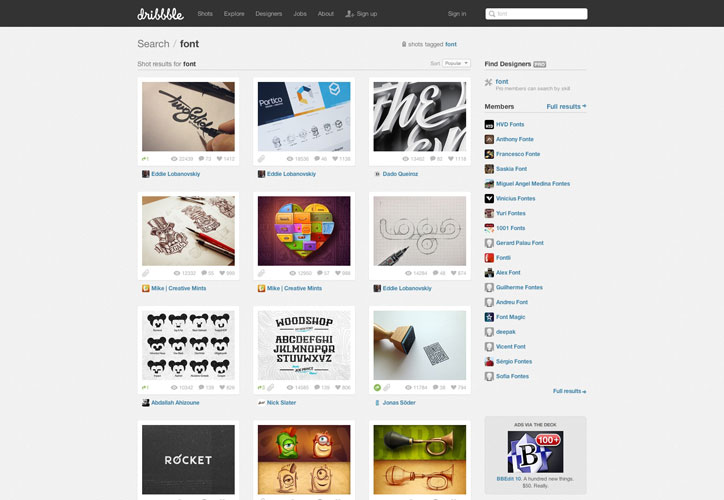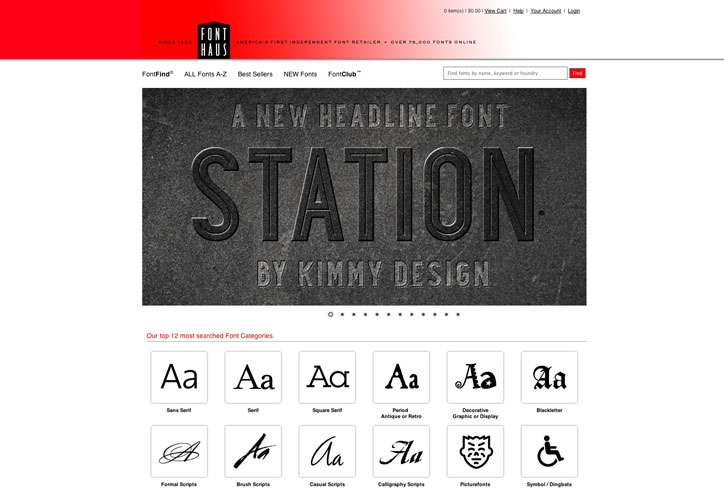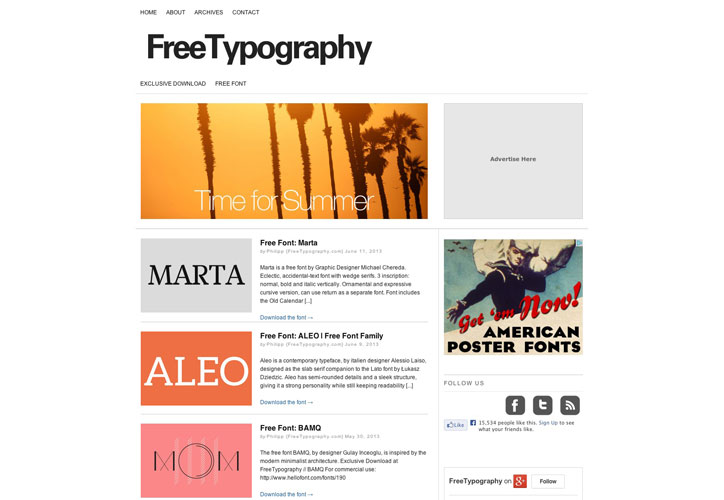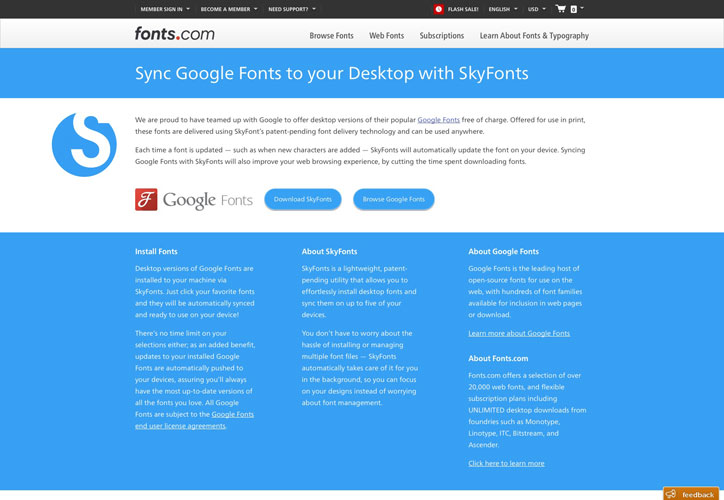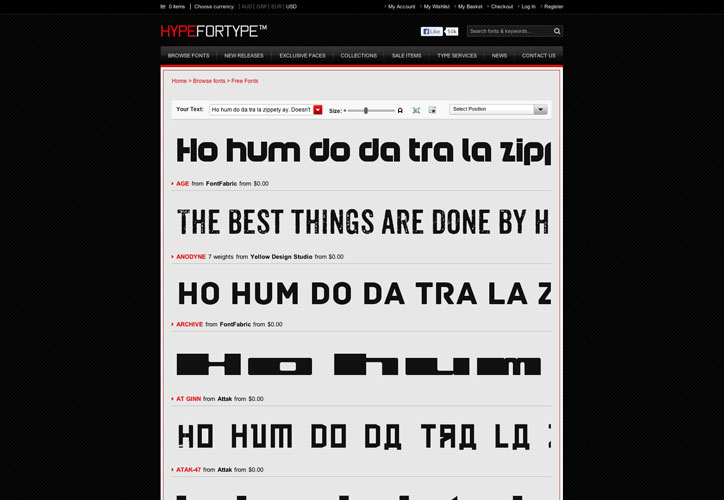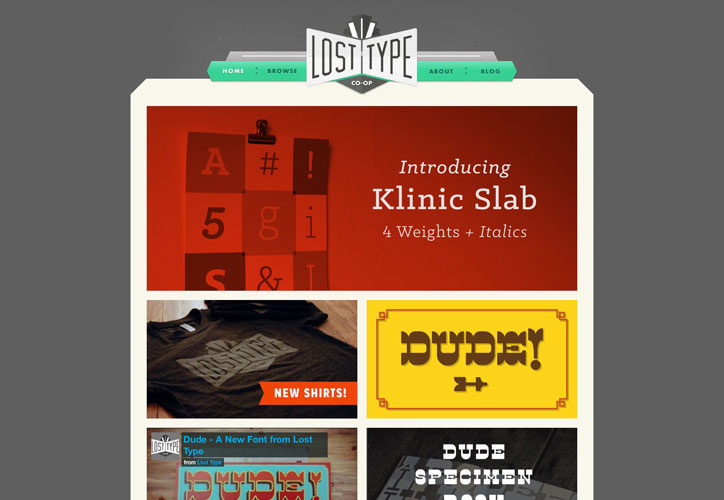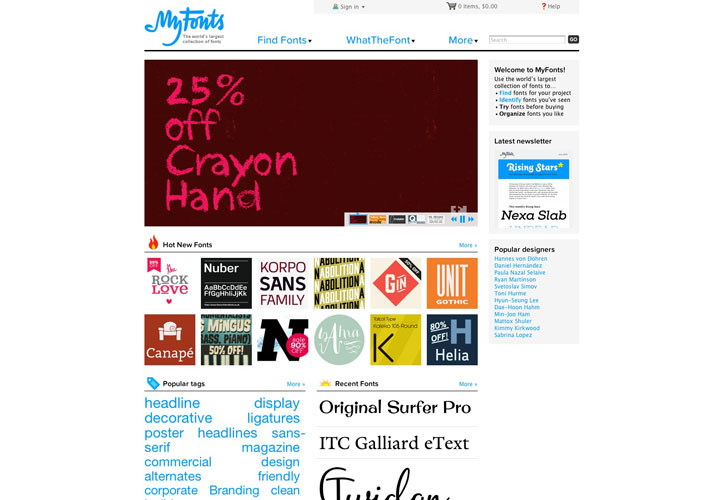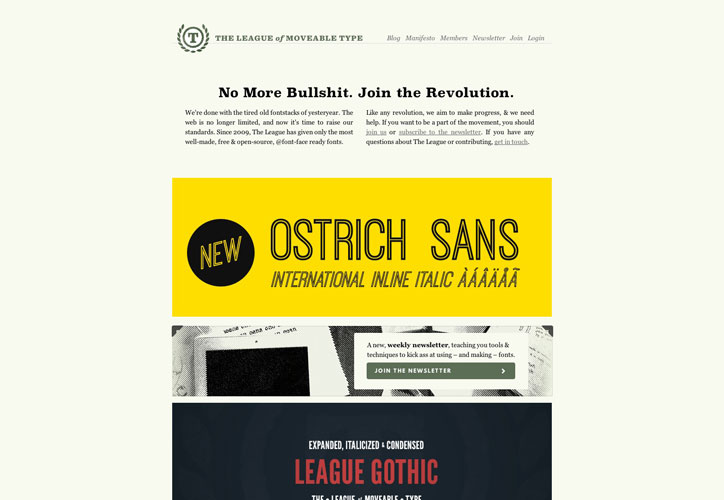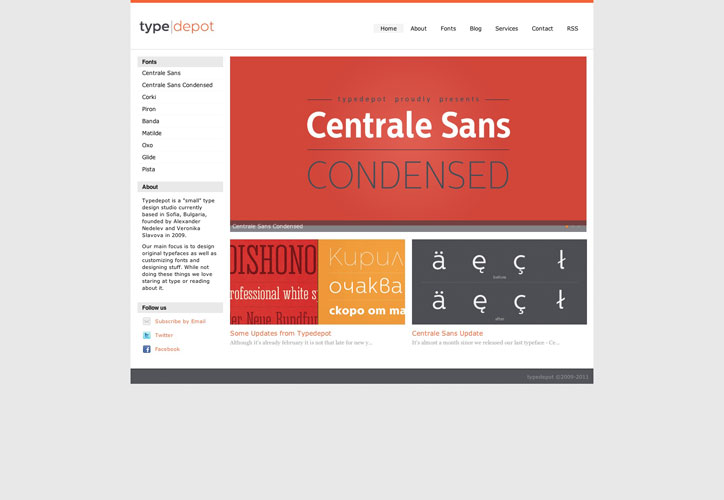
Font İndirme Siteleri
İnternette yüzlerce ücretsiz font indirme siteleri var. Burada sorun bunların çoğunda sıradan, kalitesiz fontların olması. Birçok tasarımcı bu gereksiz ve sevimsiz olan yaz tiplerini kullanmayı tercih etmiyor. Aslında önemli olan doğru ve yapılan tasarıma en uygun olan fontların bulunabileceği doğru sitelere bakmak. Tasarımcılar bilir ki yanlış kullanılan font projenin yönünü tamamen değiştirebilir. Doğru yazı tipi seçimi tasarımcı için bir görev. Çok yuvarlak bir font tasarımı çok genç; ya da çok kalın bir font, tasarımı çok kaba gösterebilir. Bu nedenle font seçimi hem amatör hem de profesyoneller için zor bir iş. Aşağıda tasarımlarda kullanılabilecek en güzel fontları bulabileceğiniz 15 font indirme sitesini bir araya getirdik. Umarız aralarında tasarımlarınız için en uygun fontları bulabilirsiniz… MyFonts Ücretsiz font arayan kişiler genelde font için ödeme yapılan sitelere pek bakmaz. Bu çok mantıklı geliyor olsa da göz ardı edilen gerçek, bu sitelerin ziyaretçilerine bazı fontların ücretsiz demolarını sunuyor olması. MyFonts bu sitelerden biri ve doğru bir arama yaptığınızda tek seferde birçok bedava font bulabilirsiniz. Google Fonts Birçok tasarımcı ücretsiz webfont’u indirmek için Google Fonts’u kullanıyor. Bu Google’ın kullanıcılarına verdiği en iyi hizmetlerden biri. Fakat burada çok fazla yazı tipi var ve arayüz bir proje için font bulmaya pek elverişli değil. Sadece webten arama yaparak uygun fontu bulabilir ve indirebilirsiniz. Fakat Fonts.com’u kullanarak herhangi bir Google fontunu kolayca indirebilir ve senkronize edebilirsiniz.
Hype For Type HFT kaliteli fontların satıldığı bir başka yaz tipi sitesidir. MyFonts’u kullandığınızda ücretsiz fontlar için bir miktar araştırma yapmanız gerekiyor. Hype For Type’te ise bu fontlar bir yerde toplanmış durumda ve rahatça indirip kullanabiliyorsunuz.
The League of Moveable Type Açık kaynak sunulmasını desteklemesi ile bilinen sitede, bazı son derece kaliteli ve trendlere uygun yazı fontlarını bulabilirsiniz.
Dribbble tam anlamıyla tasarımcılara hitap ediyor. Birçok freelance tasarımcı ofislerine ya da evlerine hapsolup kimse ile konuşamıyor. Dolayısıyla Dribbble üzerinde çalıştığınız iş hakkında feedback almak adına oldukça önemli bir kaynak.
TypeTogether İki font tasarımcının tüm dünya için en iyi yazı tiplerini oluşturmak amacıyla bir araya gelmesi sonucu kurulan sitedir. Bu tasarımcı firmalar için özel yazı tipleri yaratırken, diğer taraftan da tasarımcılar için ücretsiz fontlar sağlıyor.
Fonthaus Ziyaretçilerine ücretli ve ücretsiz fontlar sunan bir başka site. Fonthaus, en popüler ve kaliteli font sağlayıcılardan olmasa da; zevkinize uygun bir yazı tipi bulmak için biraz araştırma yapabilirsiniz.
FontStruct FontStruct, tasarımcılara kolaylıkla kendi özel fontlarını yaratmaları için yardımcı olan bir web uygulaması. Bu uygulama ile tasarımcılar kendi fontlarını bulmaları için teşvik ediliyor. Biraz karışık bir kullanımı olsa da birçok tasarımcının kullandığı bir yöntem.
Lost Type Co-Op İnsanlara benzersiz, şık, kaliteli fontlar sunmak isteyen iki kişinin kurduğu bu site ücretli ve ücretsiz yazı tipleri ile tasarımcıların tercihlerinden biri.
FreeTypography.com Herkese çok sayıda ve ücretsiz fontlar sunan bu blog, özellikle tasarımcıların mutlaka göz atması gereken bir site.
Type Depot Type Depot, Bulgaristan merkezli bir font tasarım stüdyosu. Burada çok fazla yazı tipi bulunmasa da ileriki projelerde kullanmanız açısından aklınızda bulunmalı.
Behance Dribbble’a benzeyen site, tasarımcıların işlerini göstermek için oluşturulmuş. Bu tür sitelerde arama yaparak çok geniş bir font yelpazesine ulaşabilir, projelerinize uygun fontlar tasarlayan kişileri keşfedebilirsiniz.
Font Fabric Ücretsiz font bulmak için kullanılacak en iyi yöntemlerden biri popüler font dökümanlarının araştırılabildiği siteler. Font Fabric, uygun fiyatlarla ve ücretsiz olarak ziyaretçilerine font sağlayan bu sitelerden biri. Projenize uygun bir yazı tipi bulamadıysanız buradaki yazı dökümlerini incelemenizi tavsiye ederiz.
Font Squirrel Birçok tasarımcı için ilk seçimlerden biri olan Font Squirrel’de ücretsiz olan birçok font ticari kullanım için de uygun.
Sonsuz içeriklerin yer aldığı online dünyada projenize uygun yazı tipi aramaktan sıkıldıysanız bu siteleri ziyaret edebilirsiniz. Umarız tasarımlarınız için en uygun fontu bulabilirsiniz.